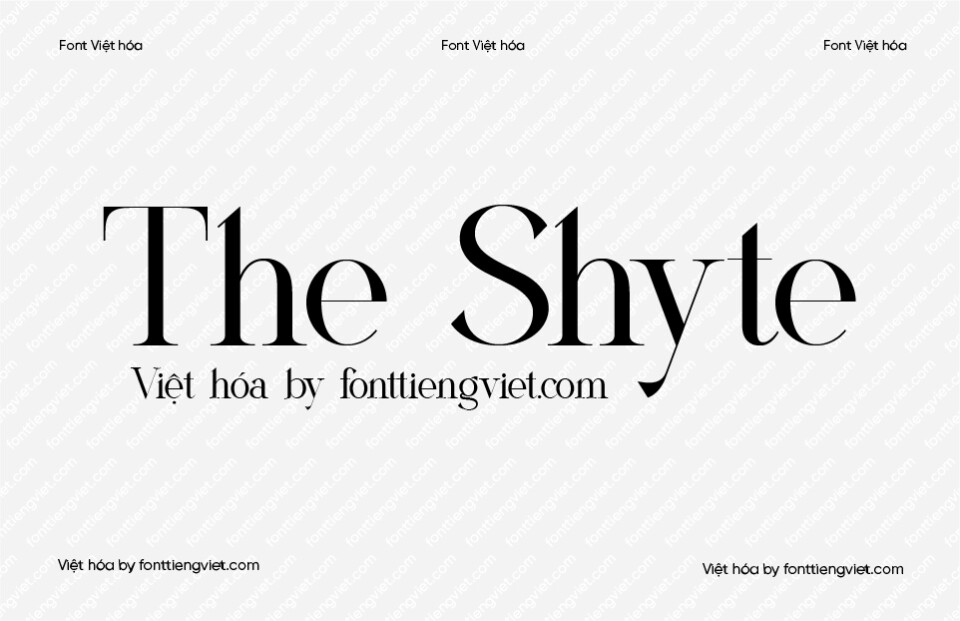
Font Việt hóa 1FTV VIP The Shyte
Font Việt hóa 1FTV VIP The Shyte – Bộ font Serif hiện đại cho thiết kế chuyên nghiệp
Giới thiệu về Font Việt hóa 1FTV VIP The Shyte
Trong thế giới đồ họa hiện nay, việc tìm kiếm một bộ Font Miễn Phí chất lượng và hỗ trợ đầy đủ tiếng Việt luôn là ưu tiên hàng đầu của các nhà thiết kế. Font Việt hóa 1FTV VIP The Shyte nổi lên như một lựa chọn hoàn hảo nhờ sự kết hợp tinh tế giữa phong cách Serif cổ điển và những đường nét cách tân mạnh mẽ. Đây là bộ phông chữ mang đậm tính nghệ thuật, giúp các tác phẩm thiết kế trở nên sang trọng và có chiều sâu hơn. Đặc biệt, phiên bản 1FTV VIP đã được tinh chỉnh kỹ lưỡng về dấu câu, đảm bảo tính thẩm mỹ cao nhất khi gõ văn bản tiếng Việt mà không gặp lỗi hiển thị.
Những đặc điểm nổi bật của bộ Font Việt hóa 1FTV VIP The Shyte
Phong cách thiết kế sang trọng và đẳng cấp
Font Việt hóa 1FTV VIP The Shyte sở hữu các chân chữ (serif) sắc nét nhưng không quá cứng nhắc, tạo cảm giác thanh thoát và uyển chuyển. Cấu trúc của chữ được tính toán tỉ mỉ để giữ được sự cân bằng giữa các khoảng trắng, giúp người xem dễ dàng tiếp nhận nội dung ngay cả ở kích thước nhỏ. Với vẻ ngoài mang hơi hướng thời thượng, bộ font này cực kỳ phù hợp cho các dự án thiết kế nhận diện thương hiệu, bìa tạp chí cao cấp hoặc các ấn phẩm thời trang cần sự lịch lãm.
Khả năng ứng dụng đa dạng trong nhiều lĩnh vực
Không chỉ dừng lại ở các thiết kế in ấn, Font Việt hóa 1FTV VIP The Shyte còn phát huy tối đa sức mạnh trong môi trường kỹ thuật số. Bạn có thể sử dụng nó để làm tiêu đề cho website, tạo các bài đăng thu hút trên mạng xã hội như Facebook hay Instagram. Nhờ bộ ký tự đa dạng và các ký tự thay thế (alternates) phong phú, người dùng có thể thỏa sức sáng tạo để tạo ra những tiêu đề độc bản, gây ấn tượng mạnh với thị giác khách hàng. Tính tương thích cao giúp font hoạt động mượt mà trên nhiều phần mềm thiết kế phổ biến hiện nay.
Lợi ích khi sử dụng Font Việt hóa 1FTV VIP The Shyte trong thiết kế
Tối ưu hóa trải nghiệm người dùng Việt
Một trong những rào cản lớn nhất khi sử dụng font ngoại quốc là lỗi font khi gõ dấu tiếng Việt. Với Font Việt hóa 1FTV VIP The Shyte, vấn đề này đã được giải quyết triệt để. Các dấu thanh được đặt ở vị trí chuẩn xác, độ dày của dấu tương đồng với nét chữ chính, giúp văn bản trở nên chuyên nghiệp và dễ đọc hơn. Điều này đặc biệt quan trọng đối với các bạn học sinh, sinh viên khi làm báo cáo thuyết trình hoặc các giáo viên khi soạn thảo giáo án điện tử cần sự chỉn chu và đẹp mắt.
Tiết kiệm thời gian và chi phí cho nhà thiết kế
Kết luận về bộ Font Việt hóa 1FTV VIP The Shyte